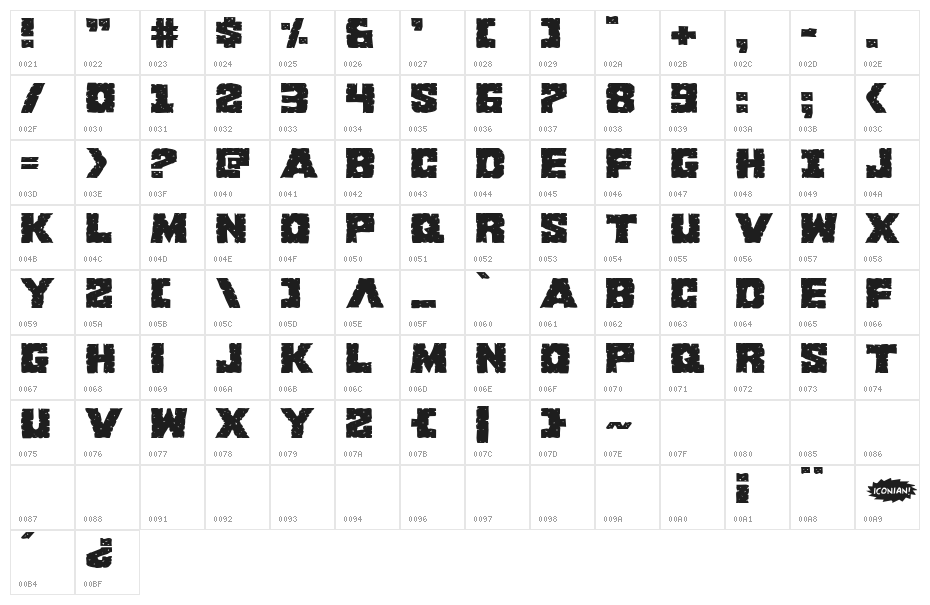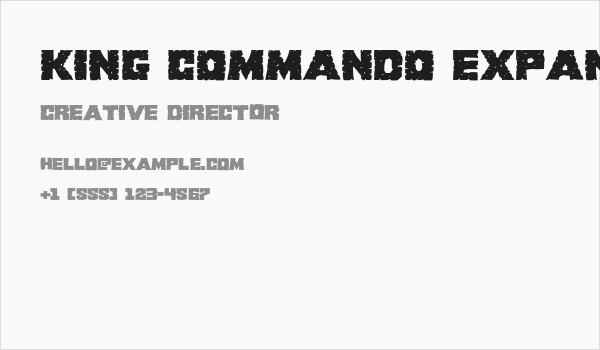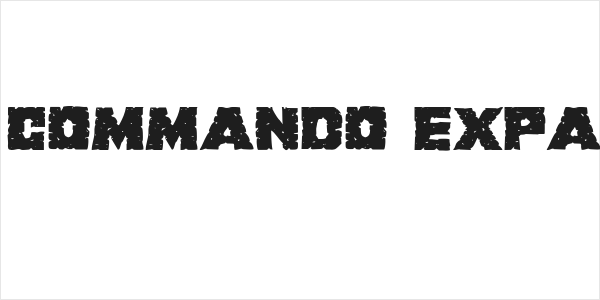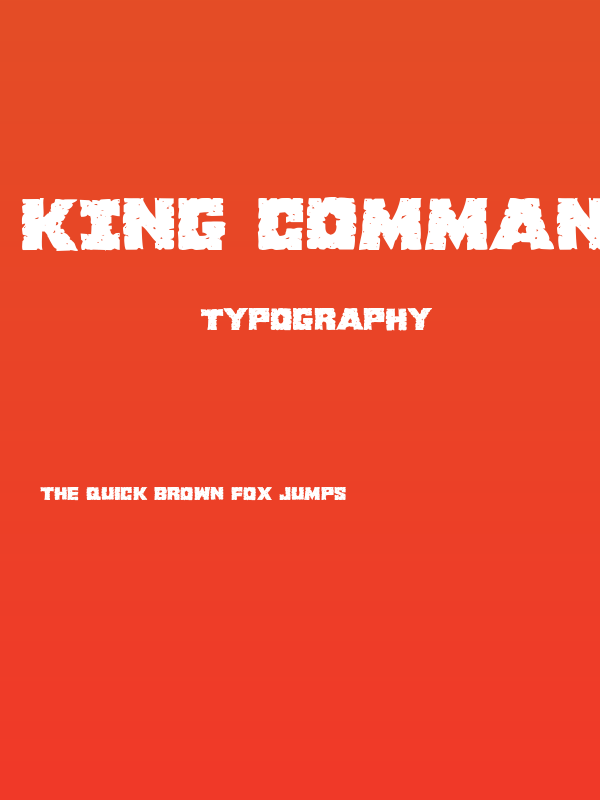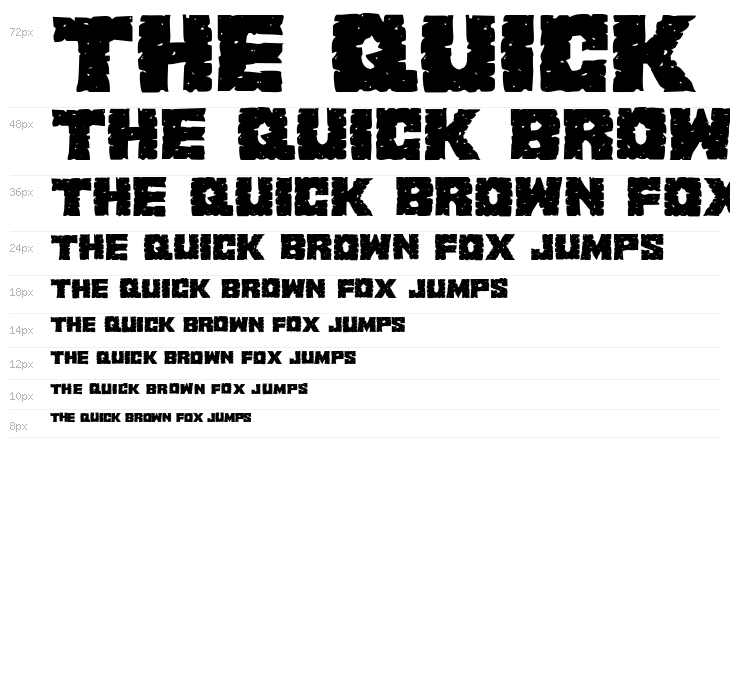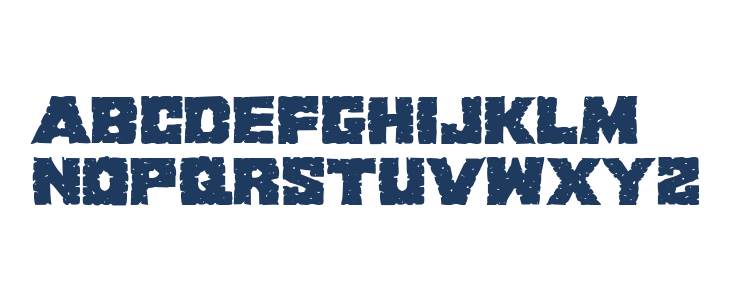
King Commando Expanded Font
✎ Distorted Eroded
| Vorgeschlagene Projekte | Ideal for military-themed posters, video game titles, action movie covers, and branding that requires a strong, authoritative presence. |